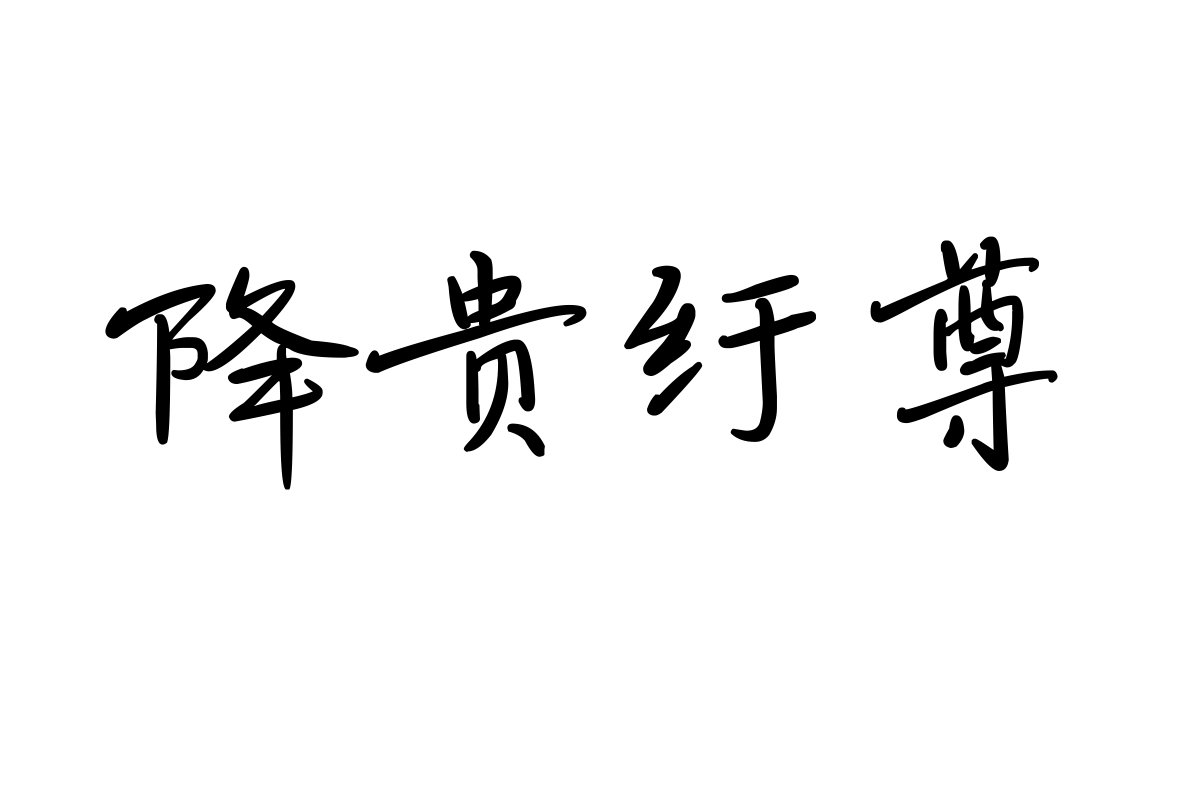
汉仪新蒂手札体是一款具有独特风格和特色的字体。它采用了手写风格的设计,线条流畅自然,给人一种亲切、温馨的感觉。这种字体适合用于各种需要表达情感和个性的场合,如贺卡、邀请函、广告等。
汉仪新蒂手札体的字形结构紧凑,笔画粗细适中,既有力度又有柔美。它的每个字都像是一个独立的小故事,通过不同的笔画组合,展现出丰富的层次感和立体感。这使得汉仪新蒂手札体在视觉上具有很强的吸引力和表现力。
此外,汉仪新蒂手札体还注重细节的处理,如字间距、行间距等都经过精心设计,使得整体布局更加协调和谐。这使得汉仪新蒂手札体在印刷和电子屏幕上都能保持良好的视觉效果。
总的来说,汉仪新蒂手札体是一款非常实用的字体,无论是用于个人创作还是商业用途,都能展现出独特的魅力和价值。